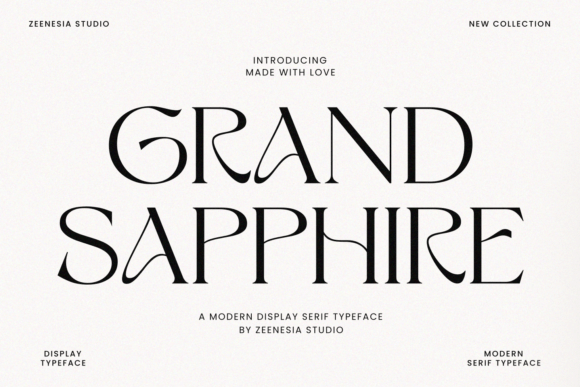
Grand Sapphire
Znalezienie odpowiednich elementów projektu może być wyzwaniem, ale Grand Sapphire oferuje wyjątkową kolekcję, która natychmiast ulepszy Twoją pracę.
Precyzyjnie wykonany, Grand Sapphire zapewnia czyste wektory, płynną typografię i licencję komercyjną dla Twojego spokoju.
Niezależnie od tego, czy tworzysz produkty POD (druk na żądanie), zaproszenia ślubne czy grafiki do mediów społecznościowych, Grand Sapphire będzie idealnym wyborem.